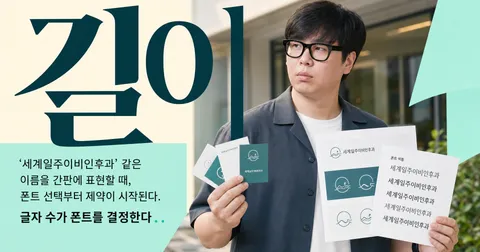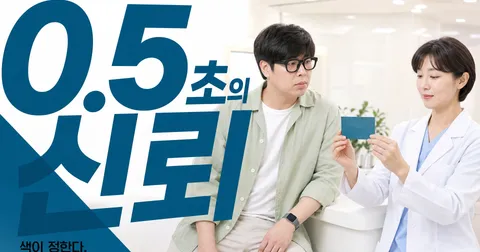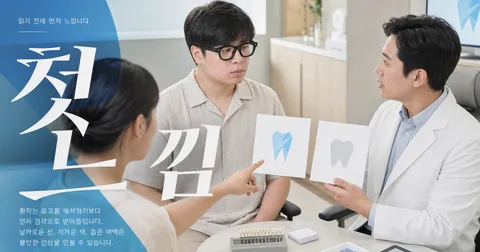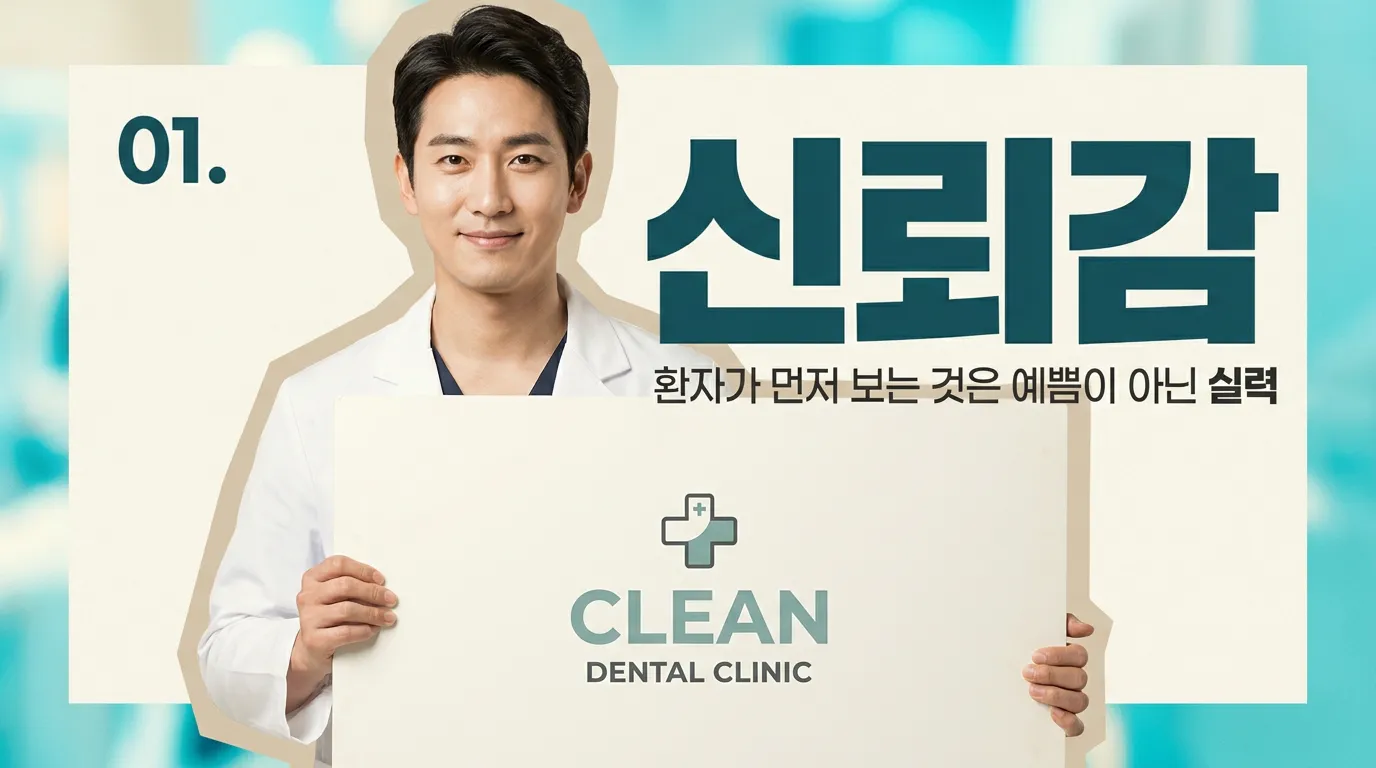
치과 로고 폰트, 환자가 ‘실력 있다’고 느끼는 7가지 기준
치과 로고 폰트 선택 전 꼭 봐야 할 실무 가이드. 믿음직해 보이는 서체와 피해야 할 서체 7가지를 정리했습니다.
환자는 로고를 보고 ‘예쁜 치과네’보다 먼저 ‘여기 내 이를 맡겨도 되나’를 판단합니다.
환자는 글자에서 뭘 먼저 읽을까요?
치과 로고 폰트는 취향 문제가 아닙니다. 환자는 글자 모양에서 진료의 태도를 먼저 봅니다. 획이 흔들리면 진료도 가벼워 보이고, 너무 얇으면 장비는 좋아도 책임감이 약해 보입니다.
Journal of Business Research에 실린 ‘Font appropriateness and brand choice’ 연구가 흥미로웠습니다. 작은 현장 실험에서 소비자는 상품과 어울리는 폰트가 붙은 초콜릿을 75% 선택했습니다. 그러니까 폰트는 장식이 아니라 ‘이 브랜드가 자기 역할을 알고 있나’를 판단하게 하는 단서입니다. (sciencedirect.com)
치과라면 답은 선명합니다. 세련된 척보다 ‘정돈된 실력’이 먼저입니다. 원장님 치과가 임플란트, 교정, 심미치료 중 어디에 강한지에 따라 무게는 달라져도, 기본은 읽히는 획과 안정된 간격입니다.
‘실력 있어 보이는’ 치과 서체는 어디가 다를까요?
저라면 먼저 한글 자소의 구멍을 봅니다. ㅇ, ㅎ, ㅁ 안쪽이 답답하지 않아야 합니다. 대기실 유리문, 네이버 플레이스 썸네일, 진료복 자수처럼 작게 줄었을 때도 이름이 살아야 하니까요.
추천하는 방향은 휴머니스트 산세리프 또는 약간 단단한 고딕 계열입니다. 획 굵기는 Light보다 Medium에 가깝게. 글자 간격은 살짝 열고, 장평은 억지로 좁히지 않습니다. ‘서울미소치과’ 같은 이름에서 미소를 둥글게 풀어도, ‘치과’ 두 글자는 또렷하게 잡아야 합니다.
SAGE에 실린 서체 인상 연구에서도 세리프는 전통적으로, 산세리프는 캐주얼하게 읽히는 경향이 확인됩니다. 저는 이걸 치과에 그대로 대입하지는 않습니다. 다만 ‘환자가 어떤 성격을 먼저 느끼는가’는 분명히 서체에서 출발합니다. (journals.sagepub.com)
피해야 할 서체 7가지는 뭘까요?
첫째, 손글씨체. 소아치과 일부를 빼면 진료보다 이벤트처럼 보입니다. 둘째, 초경량 얇은 폰트. 고급스러워 보이려다 작은 화면에서 사라집니다. 셋째, 과한 명조체. 법무법인이나 장례식장 쪽 인상이 섞일 수 있습니다.
넷째, 장평을 심하게 줄인 고딕. 바쁜 상가 간판처럼 보입니다. 다섯째, 기울임체와 스크립트체. 치과 이름이 ‘서명’처럼 읽히면 의료기관보다 개인 숍에 가까워집니다.
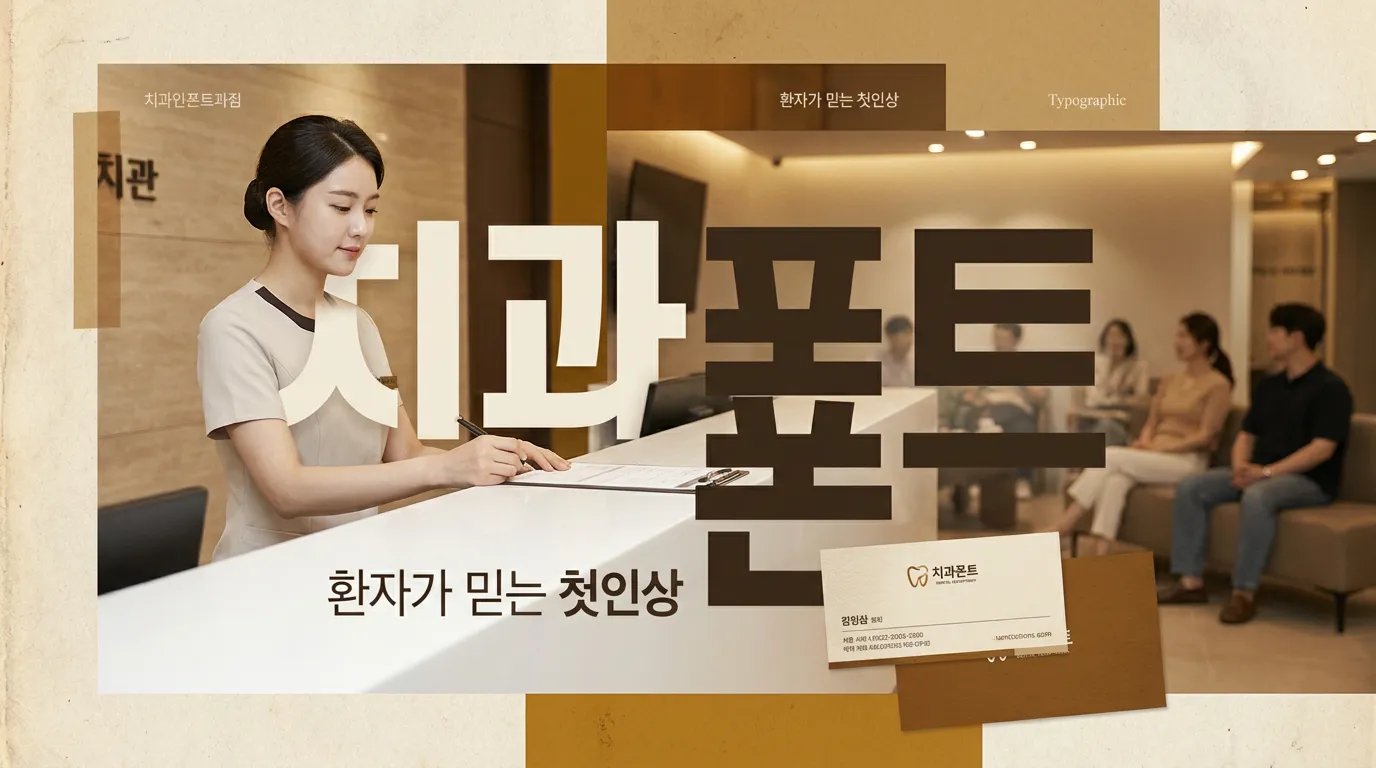
여섯째, 무료 폰트를 그대로 쓴 느낌. 폰트 자체가 나쁜 게 아니라, 다들 쓰는 모양 그대로면 치과의 고유한 기억점이 없습니다. 일곱째, 자소를 과하게 자른 실험형 서체. 멋은 있는데 처음 보는 환자가 한 번에 못 읽습니다. 의료 브랜드에서 ‘해독’은 손해입니다.
그럼 로고 폰트는 어떻게 고르면 될까요?
3단계로 보면 됩니다. 먼저 이름을 2초 안에 읽을 수 있는지 봅니다. 다음으로 ‘치과의원’까지 붙였을 때 무게가 무너지지 않는지 봅니다. 마지막으로 모바일 썸네일 크기로 줄여봅니다. 여기서 흐려지면 실제 접점에서도 약합니다.
국가법령정보센터의 의료법 시행규칙 제40조를 보면, 의료기관 명칭표시판은 고유명칭과 의료기관 종류 명칭의 글자 크기까지 다룹니다. 로고 디자인 규정은 아니지만, 의료기관의 글자는 환자에게 정보를 정확히 전달해야 한다는 뜻으로 읽어야 합니다. (law.go.kr)
마크에서 치과 로고를 잡을 때도 예쁜 한 컷보다 이 테스트를 먼저 합니다. ‘큰 화면에서 멋진가’보다 ‘작아져도 원장님의 진료 기준이 남는가’를 봅니다.